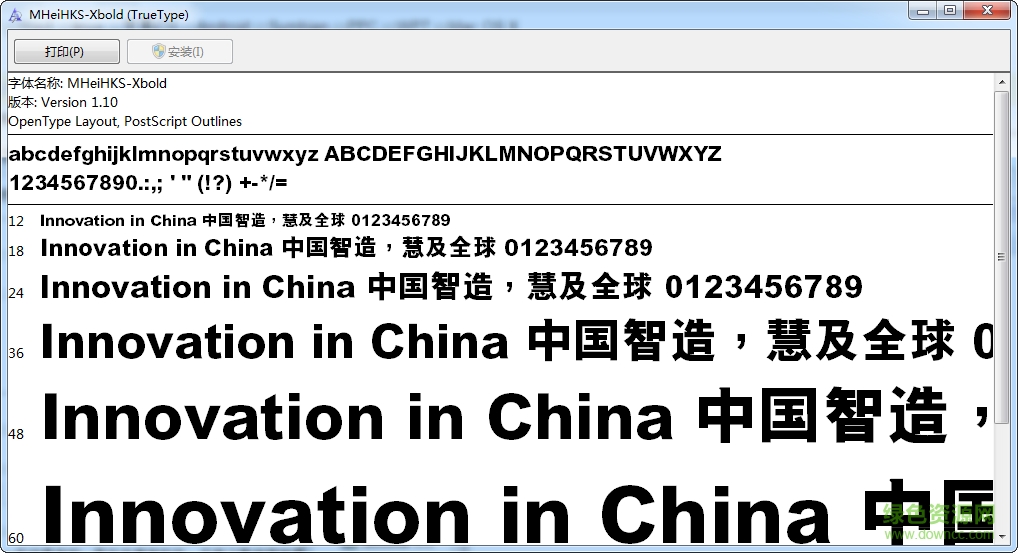
蒙納簡(jiǎn)粗黑字體是專(zhuān)為Windows系統(tǒng)提供的一款字體更換軟件,采用了蒙納簡(jiǎn)粗黑字體,字型非常粗,總體干凈利落,可應(yīng)用于廣告設(shè)計(jì)、平面設(shè)計(jì)等場(chǎng)合,歡迎來(lái)綠色資源網(wǎng)下載!